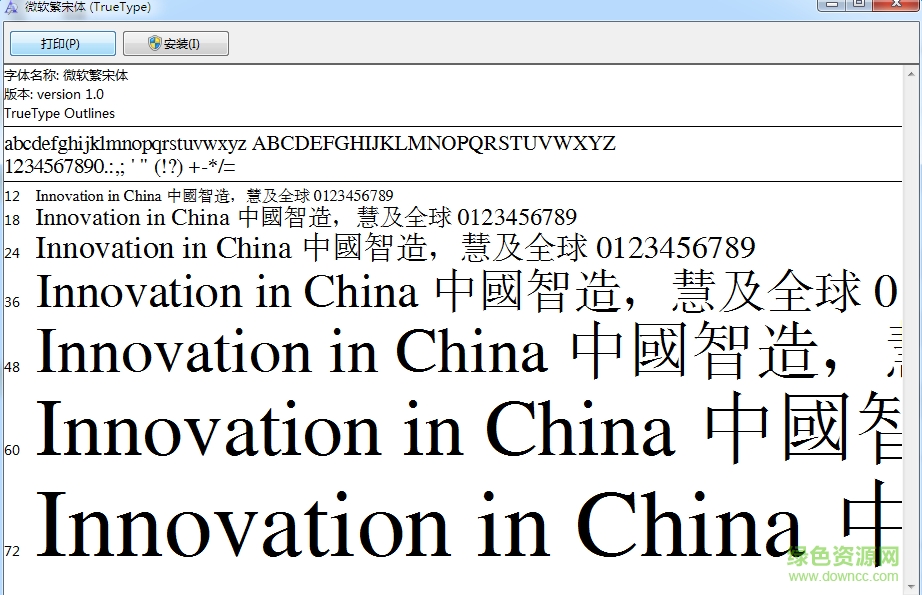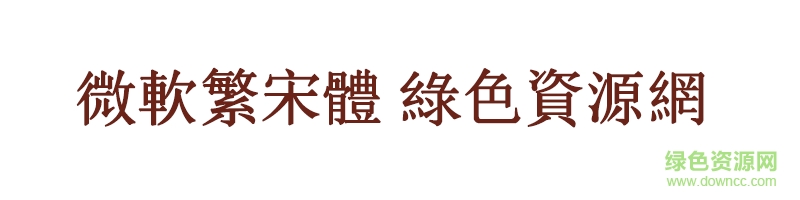
微軟繁宋體是一款基于中國書法字體宋體衍生而來的一款電腦字體,具備宋體橫輕豎重,橫線尾和直線頭呈三角狀,字形端正、剛勁有力的特點,有喜歡的朋友可以來綠色資源網(wǎng)下載!
微軟繁宋體是一款應(yīng)用于平面設(shè)計方面的中文繁體字體,該字體端正大方,一筆一畫非常正氣,整體效果出眾,可適用于廣告設(shè)計、平面設(shè)計、印刷包裝等領(lǐng)域!